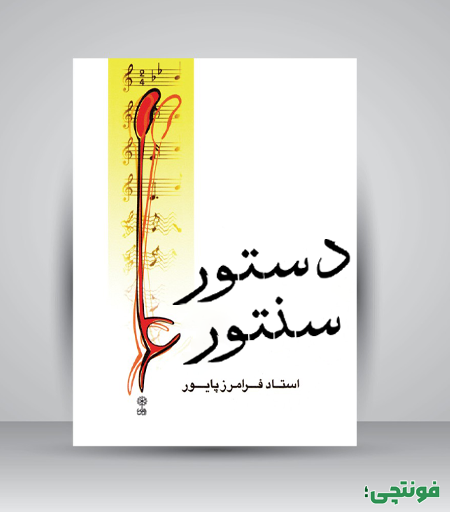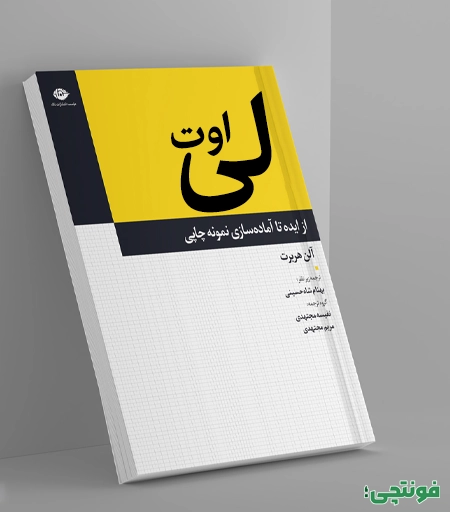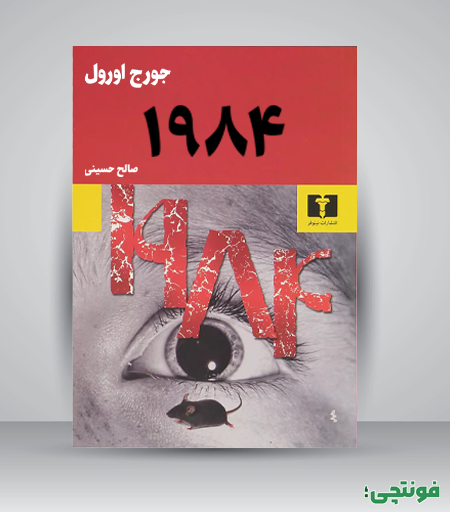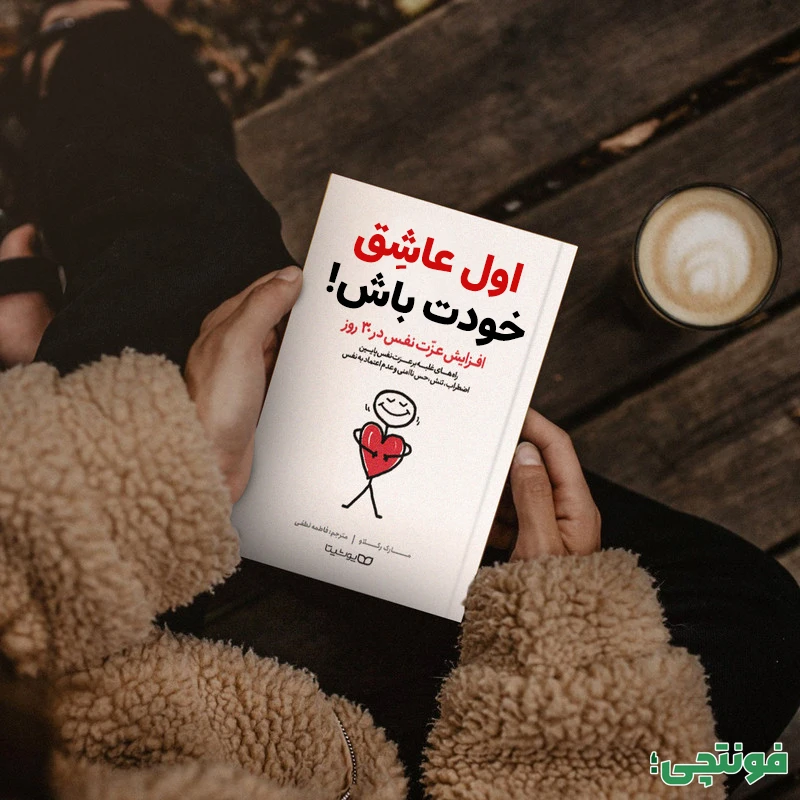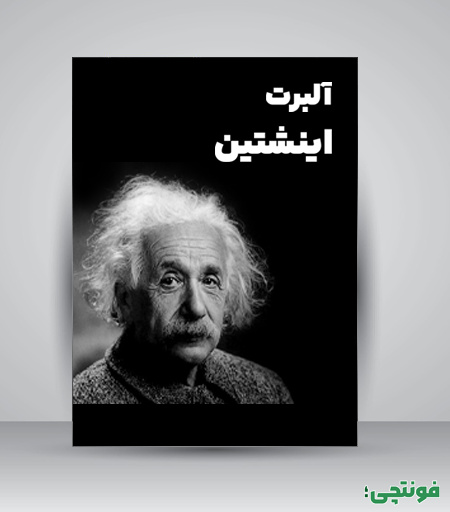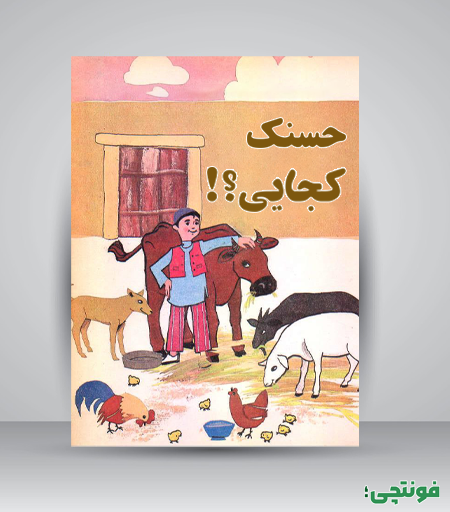
بهترین فونت برای جلد کتاب [فونت مناسب نام کتاب]
جدایی از طراحی مناسب جلد کتب، انتخاب فونت مناسب برای نام کتاب از اهمیت بالایی برخوردار است؛ چرا که جلد کتاب اولین چیزی است که چشم مخاطب را درگیر کرده و میتواند باعث جلب توجه شود. به همین جهت انتخاب بهترین فونت برای جلد کتاب یکی از موضوعات مهم در صنعت چاپ کتب است که باید به آن توجه داشت.
در این مقاله از وبلاگ فونتچی به بررسی عوامل مهمی که در انتخاب فونت خوب برای عنوان کتاب موثر هستند پرداخته و سپس تعدادی از بهترین فونتهای مناسب جلد کتاب و مجلات را با هم بررسی خواهیم کرد. این مطلب در خصوص عناوین کتابهای فارسی است.
نکات و عوامل موثر انتخاب فونت مناسب برای نام کتاب
در انتخاب فونت مناسب برای جلد کتاب، عوامل مختلفی باید در نظر گرفته شود. از جمله این عوامل میتوان به موارد زیر اشاره کرد:
- موضوع کتاب: نوع فونت باید با موضوع کتاب هماهنگی داشته باشد. برای مثال، برای کتابهای علمی و دانشگاهی، فونتهای ساده و خوانا مناسبتر هستند. در مقابل، برای کتابهای داستانی و رمان، میتوان از فونتهای فانتزی و برای کتابهای تاریخی نیز از فونتهای قدیمی که حس نوستالژی دارند استفاده کرد.
- مخاطب هدف: فونت باید با مخاطب هدف کتاب نیز هماهنگی داشته باشد. برای مثال، برای کتابهای کودکان، فونتهای بزرگ و خوانا مناسبتر هستند و ترجیحا باید از قلمهایی استفاده کرد که شکل و ساختار حروف طوری نباشد که کودکان نتوانند آن را بخوانند. در مقابل، برای کتابهای بزرگسالان، میتوان از فونتهای کوچکتر و پیچیدهتر استفاده کرد.
- اندازه فونت: اندازه فونت باید به گونهای باشد که از فاصله دور نیز قابل خواندن باشد. بهطوری که مخاطب بتواند از فاصله چند متری عناوین را خوانده و نگاه وی را جذب کند.
- رنگ فونت: رنگ فونت نیز مقولهای است که در حیطه طراحی قرار میگیرد که مهمترین نکته آن هماهنگی با رنگ پس زمینه است.
بهترین فونت برای جلد کتاب و نام کتاب
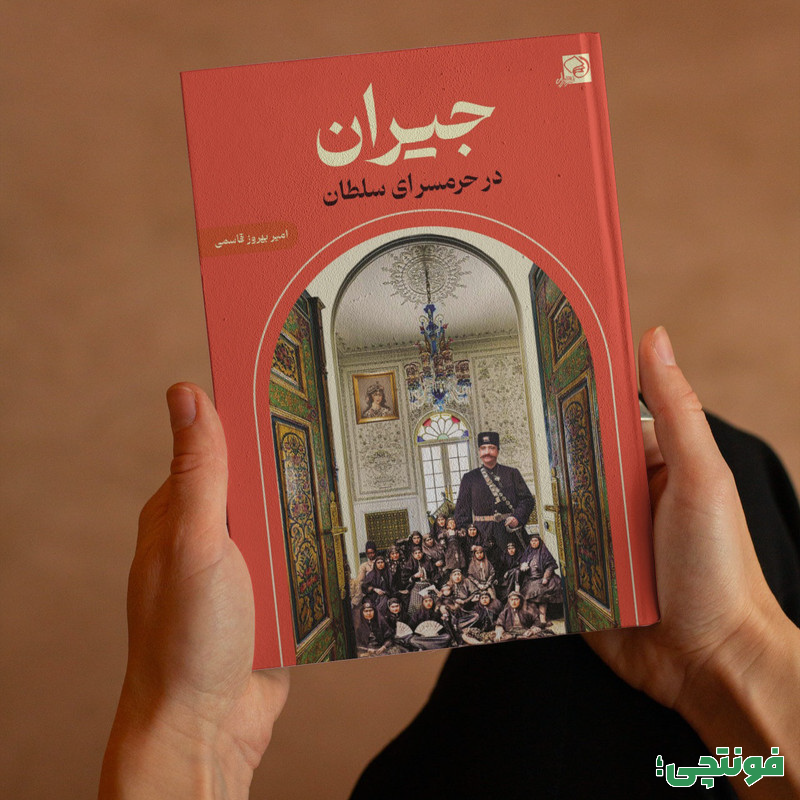
فونت دوران برای کتابهای فرهنگی، تاریخی و هنری
اگر به دنبال فونت نستعلیق برای طراحی جلد کتاب هستید فونت دوران میتواند یک انتخاب عالی باشد که با تلفیقی از این خط و خط نسخ طراحی شده است. این فونت در چند وزن متعدد در دسترس است که ظاهری دوستانه و صمیمی به کتابها خواهد داد.
در این فونت نقاط به صورت پیوسته طراحی شدهاند و از آنجا که ضخامت فونت در منحنیها، چشمیها، اتصالات و بخش پایانی حروف و نقطهها به مویی بند است، به یک فونت مناسب عنوان تبدیل شده که میتواند بیشترین اثرگذاری را در درگیر کردن مخاطب و جلب توجه به خود داشته باشد.
- ضخامت و ساختار فونت: این فونت در چندین وزن مختلف تشکیل شده است که دارای وزن نازک تا سیاه است. وجود وزنهای متعدد کمک میکند تا علاوه بر فونت عنوان کتاب، از وزنهای نازکتر برای ذکر نام نویسنده، مترجم و دیگر مشخصات کتاب استفاده کنید.
- ظاهر فانتزی و نستعلیق: دوران فونتی بر پایه سبک خط نستعلیق است که با خط نسخ تلفیق شده است. از همین جهت یک فونت عالی از نظر ظاهری مدرن و معاصر است که طرفداران بسیار زیادی دارد. ظاهر این فونت فانتزی بهنظر میرسد که با وجود سبک نقطه گذاری خاصش در جلب توجه مخاطب بسیار موثر است.
از این فونت میتوان برای انواع کتابهای فرهنگی و هنری، تاریخی و داستانی استفاده کرد که با توجه به تاریخچه و سبکی که این فونت دارد ظاهر عالی به جلد کتاب خواهد داد. خصوصا برای کتابهایی همچون فال حافظ و اشعار شاعران بزرگ که نقش یک فونت ارزشمند را بهخوبی ایفا خواهد کرد.
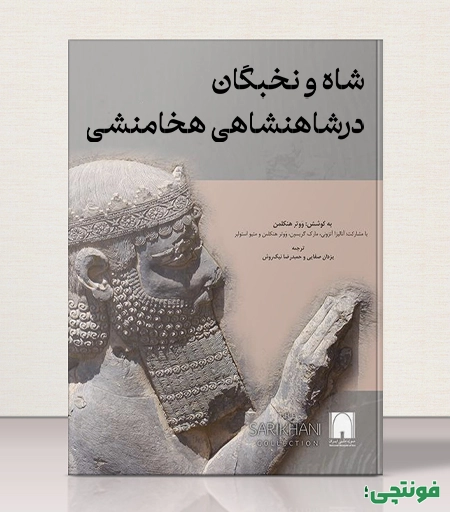
فونت گرامافون برای کتاب های تاریخی و ادبیات
فونت گرامافون یک فونت کلاسیک است که حس و حال نوستالژیک قرن بیستم را القا میکند. این فونت با ساختار کلاسیک میتواند برای استفاده در جلد کتابهای تاریخی و ادبیات کلاسیک ارتباط نزدیکی داشته باشد. از این رو، استفاده از آن برای چاپ جلد روی کتاب تاریخی میتواند گزینه مناسبی باشد.
ضخامت و خوانایی مناسب این فونت در کنار ۴ سبک خاص حروف شکل زیبایی به آن داده و همچنین برای خوانایی کاملا ایدهآل است. وجود طرههای تزئینی در حروفی مانند «الف، ط، ظ، ک، گ، ل» نیز تا حدودی فونت را فانتزی کرده که میتواند با خودنمایی و جلب توجه مخاطب را به خود جذب کند.
برخی ویژگیهای بارز توجه این فونت عبارتند از:
- ضخامت و خوانایی مناسب: فونت گرامافون دارای ضخامت مناسبی است که حروف نیز در آن به شکل کشیده طراحی شدهاند. هر دو این عامل به خوانایی بهتر عنوان کتاب از فواصل دور کمک میکند.
- ظاهر کلاسیک و اصیل: فونت گرامافون دارای ظاهری کلاسیک و اصیل است که میتواند حس و حال تاریخی کتاب را به مخاطب منتقل کند. خصوصا در مورد کتابهای تاریخ معاصر که در بیشتر فیلمها و سریالهای تاریخی چنین سبک قلمی را دیدهایم.
- تنوع سبکهای مختلف: فونت گرامافون در ۴ سبک مختلف طراحی شده که حروف دارای سبک استایل چرک، سنگی، تمیز و تمیز متحل هستند.
این فونت صرفا برای کتابهای تاریخی، ادبی و فرهنگی مناسب نبوده و میتوان از آن برای جلد سایر کتب نیز استفاده کرد. خصوصا کتابهای آموزشی که در حوزه هنر و موسیقی هستند. همنام بودن این فونت با گرامافون نیز بی دلیل نیست.
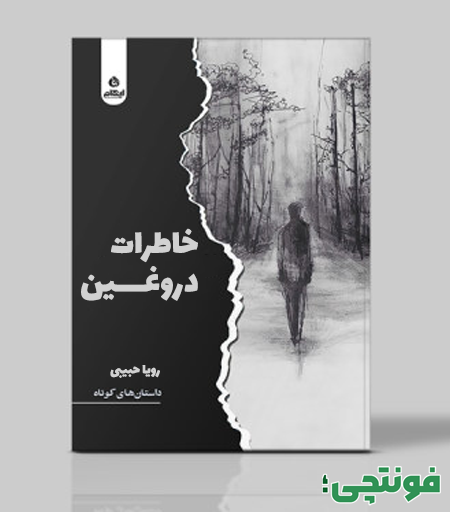
فونت لاله زار برای جلد کتاب
فونت لاله زار یک فونت فارسی است که از سبک نوشتار روزنامههای دهههای چهل و پنجاه شمسی الهام گرفته است. این فونت با ظاهر کلاسیک و نوستالژیک، میتواند حس و حال گذشته را به مخاطب منتقل کند.
فونت لاله زار دارای ویژگیهایی است که آن را برای استفاده در جلد کتابهای با حال و هوای سنتی و نوستالژیک مناسب میسازد. این فونت دارای ضخامت و خوانایی بالایی است و به راحتی در فواصل دور قابل خواندن است.
- ضخامت و خوانایی مناسب: لاله زار فونتی با وزن ضخیم است که تمامی حروف ظاهری منحنی شکل و نرم دارند. از اینرو خوانایی لازم را از فواصل دور خواهد داشت.
درود، وقتتون بخیر
عطف کتاب: بسته به ضخامت کتاب بین ۱۴ تا ۳۰ pt باشه. عنوان بزرگتر، نویسنده کوچکتر. همچنین حتما حاشیه ۳-۵ میلیمتر از هر طرف بذارید تا موقع برش خوانا بمونه.
نام نویسنده روی جلد جلو: ۲۰ تا ۵۰ pt (معمولا نصف یا کمتر از سایز عنوان کتاب).
پشت کتاب و خلاصه: ۹ تا ۱۲ pt (بهترین ۱۰-۱۱ pt برای خوانایی). فونت ساده و خوانا (مثل نازنین/زر/لوتوس)، نه خیلی کوچک.
یک نکته مهم اینکه اندازه دقیق بستگی به قطع کتاب، طراحی و سلیقه طراح داره، اما اولویت همیشه خوانایی از فاصله ۳۰-۵۰ سانتیمتری هست. همچنین حداکثر از ۲ فونت متفاوت استفاده کنید.